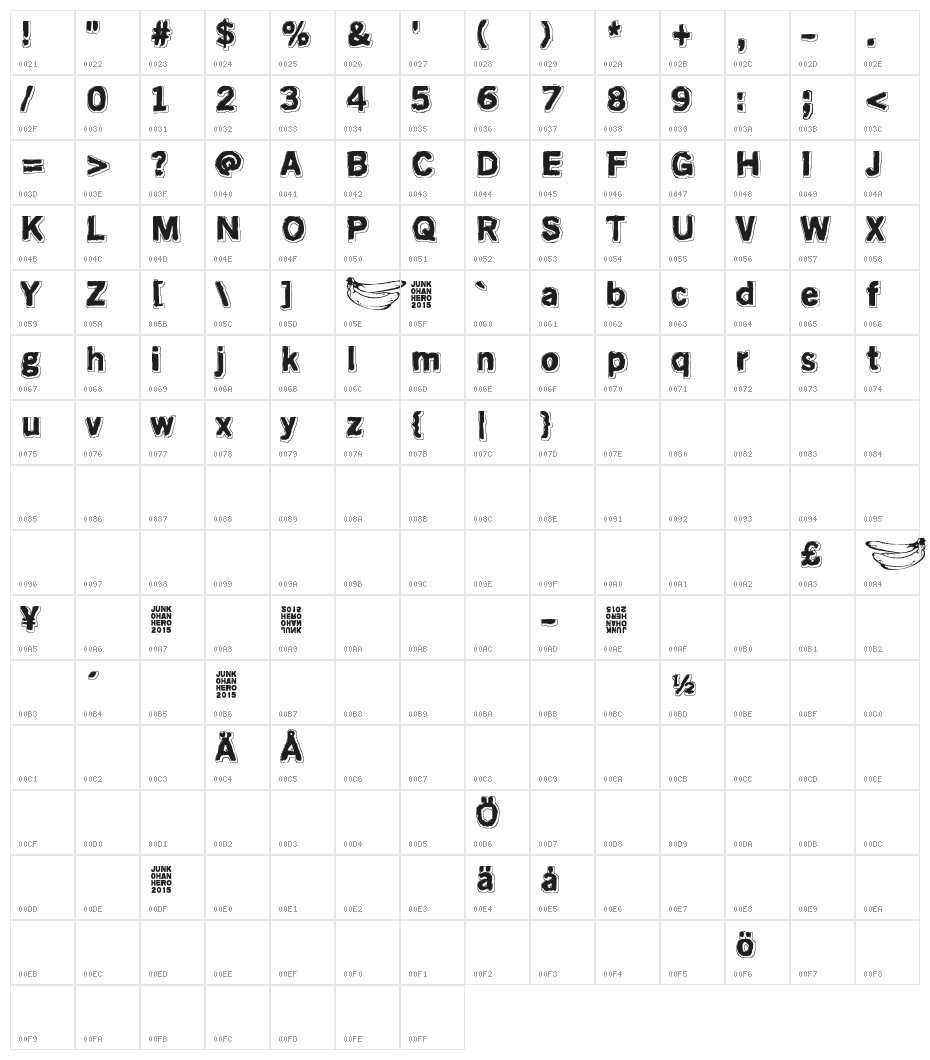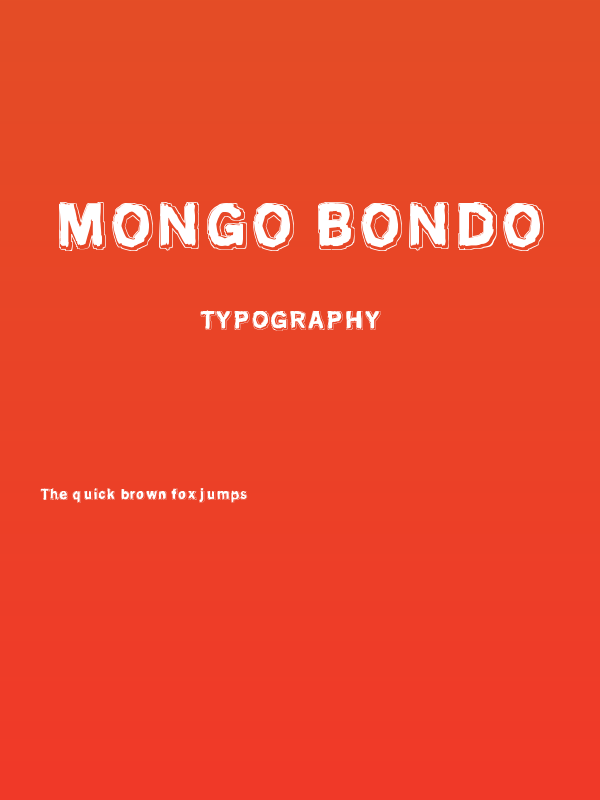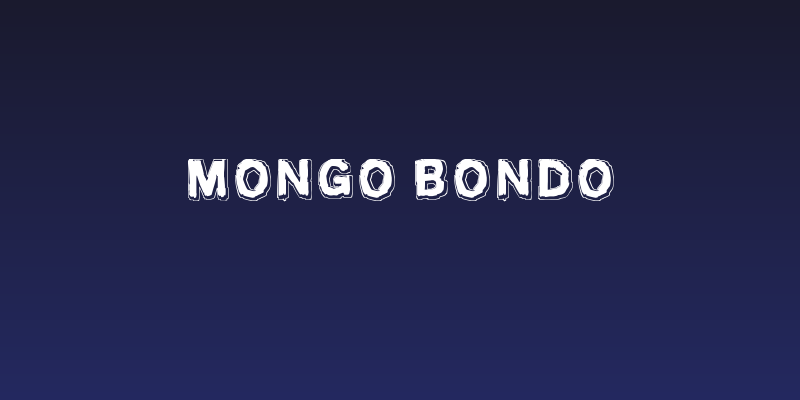
Mongo Bondo Font
| Stile generale | Playful, Whimsical |
| Caso d'uso | Headlines, Posters, Branding |
| Progetti proposti | Ideal for children's books, comic strips, playful branding, posters, and creative projects that require a fun and engaging typeface. |